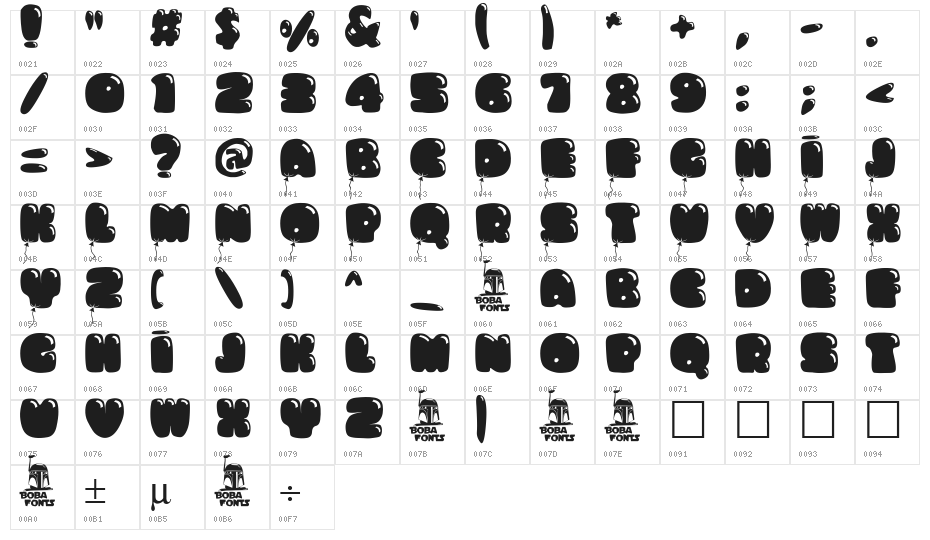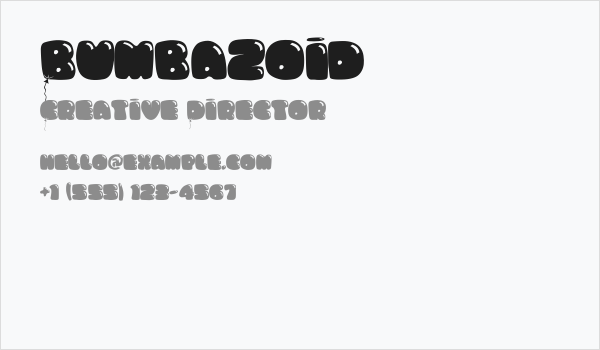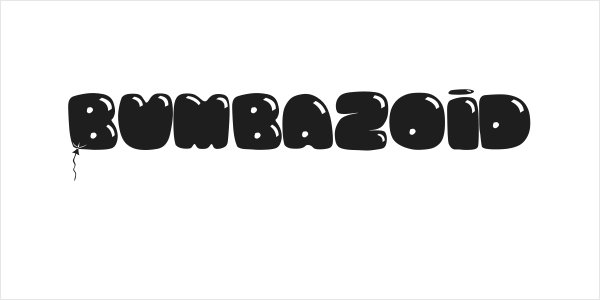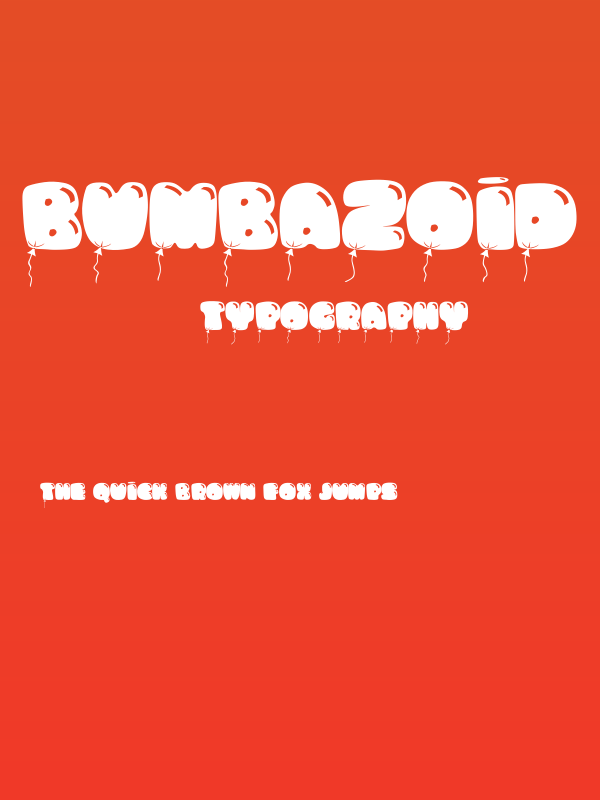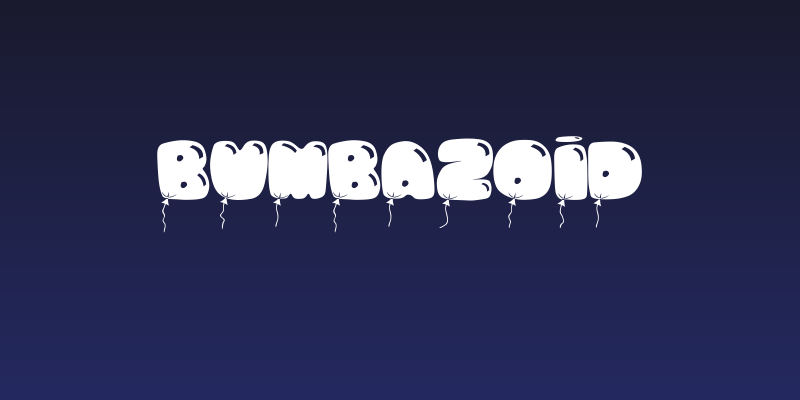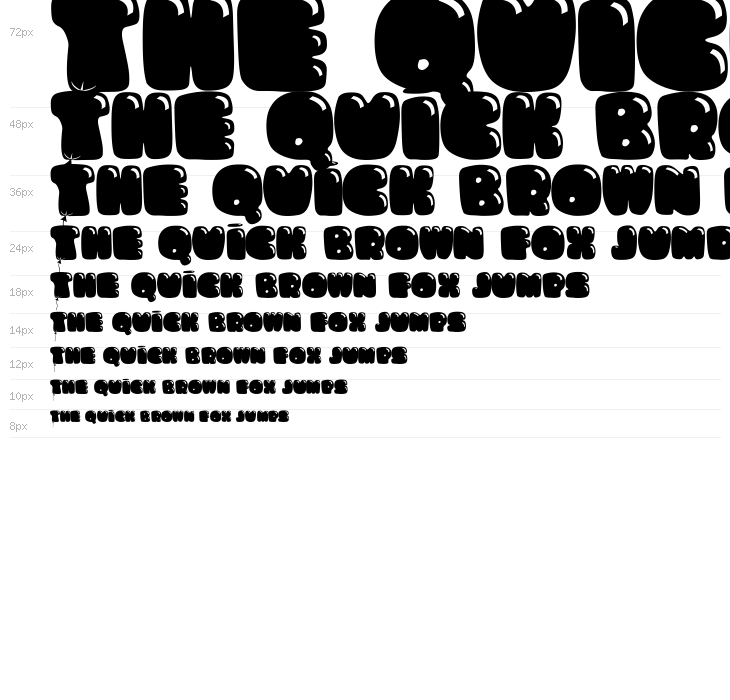
Bumbazoid Font
| Style général | Playful, Whimsical |
| Projets proposés | Ideal for children's party invitations, playful branding, festive posters, and any design needing a joyful touch. |